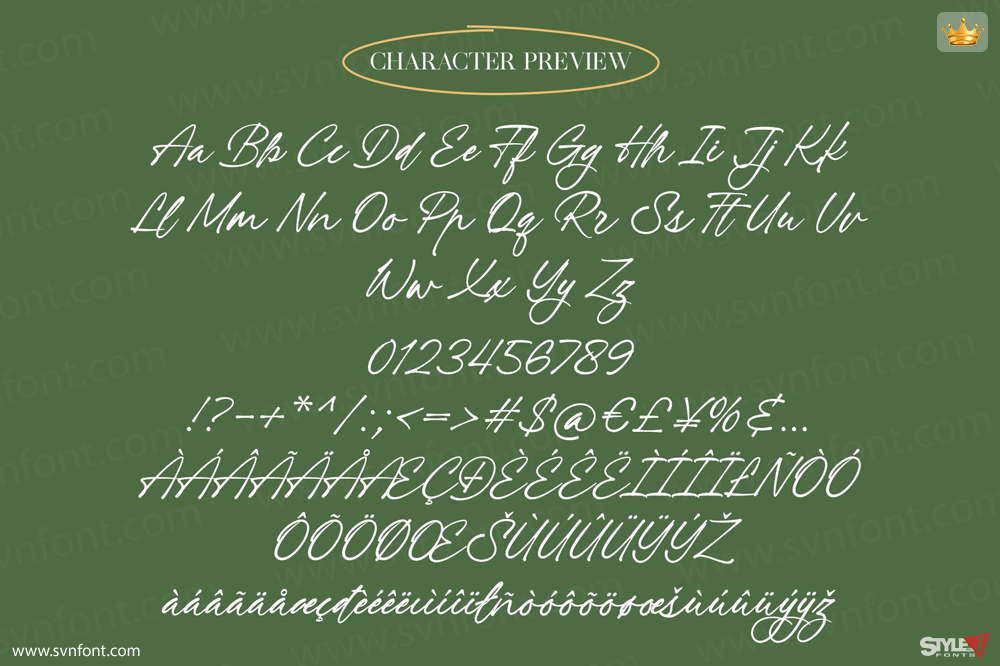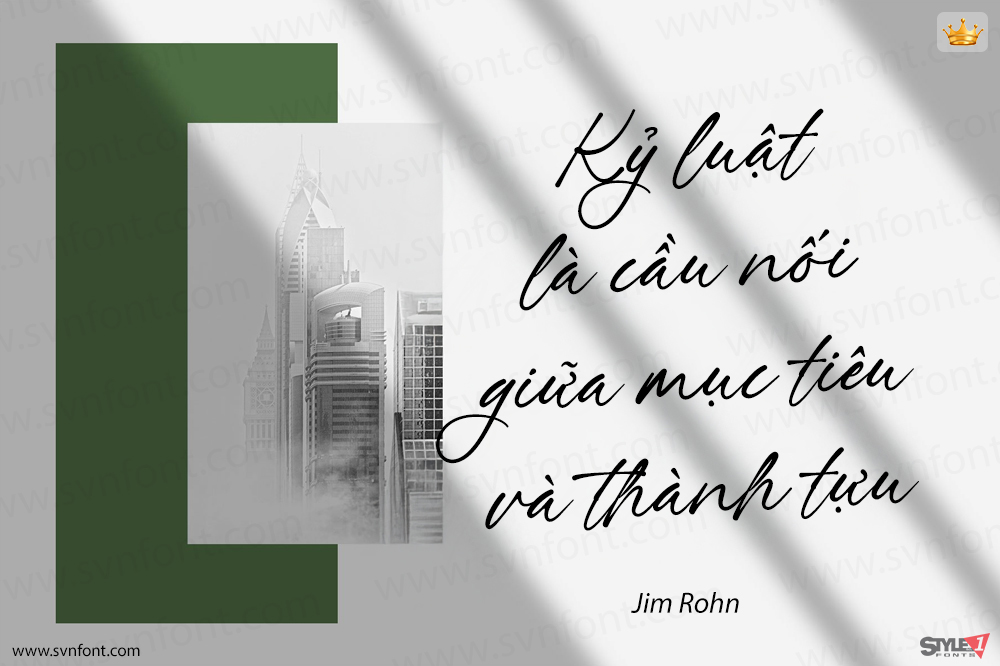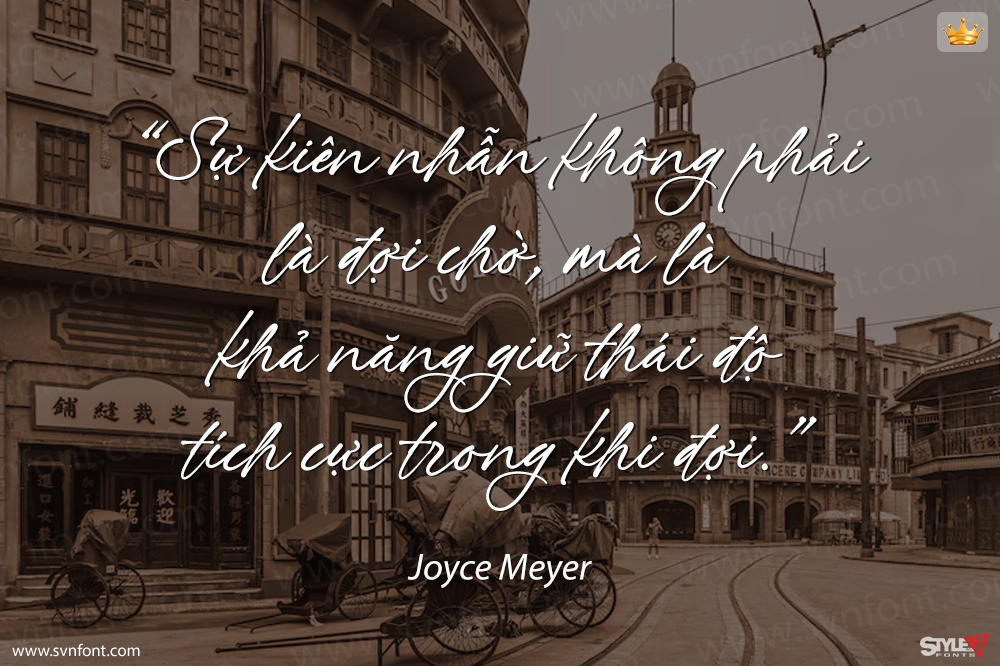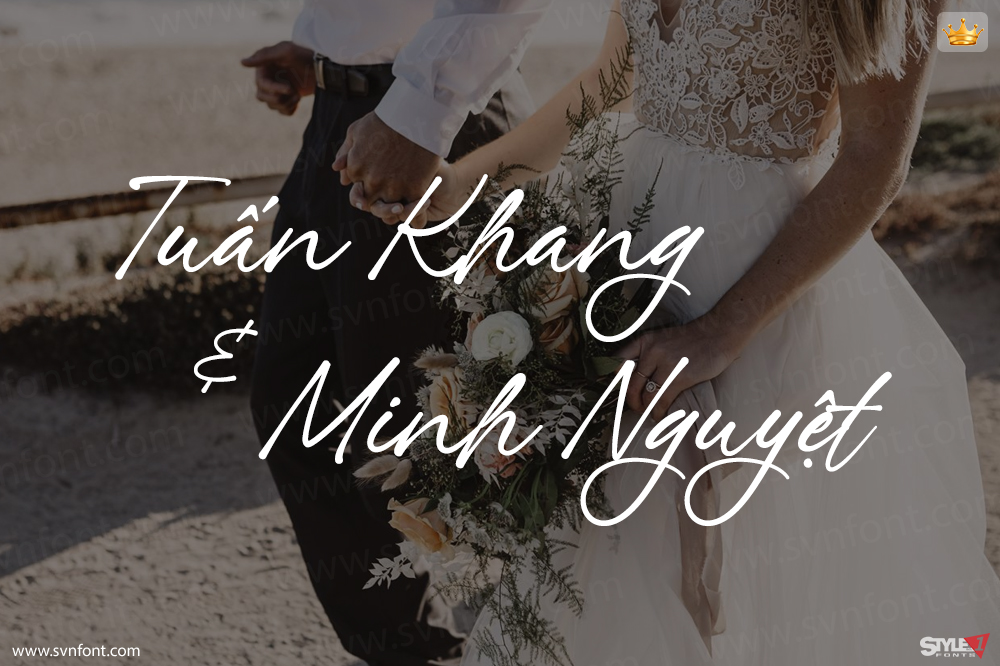
Sophitaly Script là một phông chữ theo kiểu chữ viết tay với vẻ ngoài tự nhiên và hiện đại, được thiết kế để ưu tiên tính thực tế và linh hoạt. Phông chữ này có các nét chữ rõ ràng và các hình dáng chữ cái được chế tác tỉ mỉ, tạo ra một ấn tượng chuyên nghiệp, hoàn hảo cho nhiều dự án thiết kế khác nhau. Sophitaly Script lý tưởng để sử dụng trong logo, xây dựng thương hiệu, thiết kế bao bì, bài xã luận và nhiều dự án sáng tạo khác.
Nhà thiết kế: Dwi Ahidian
Nhà phát hành: Lemonthe